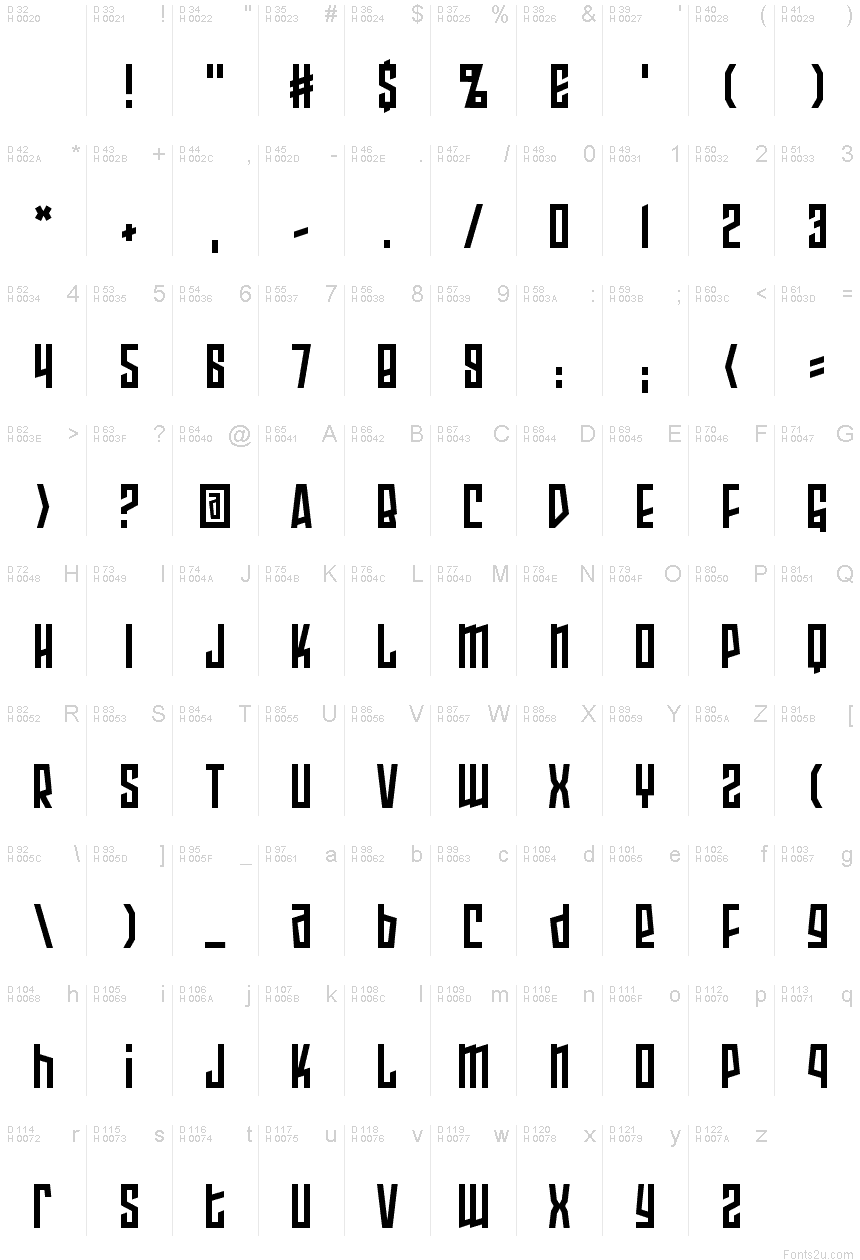
Armor Piercing 2.0 BB od Nate’a Piekosa to darmowy, retro font display o ostrym, arcade'owym charakterze. Wysokie, kanciaste kształty i ciasny, mechaniczny rytm nadają każdemu słowu wygląd tłoczonego metalu – jest odważny, zwarty i nieco drapieżny, przypominając opakowania starych gier lub komiksowe efekty dźwiękowe wycięte z czarnego winylu.
Armor Piercing 2.0 BB świetnie sprawdza się na okładkach komiksów, w grafice esports, tytułach plakatów, menu gier, miniaturach YouTube, projektach naklejek i na merchu. Ten darmowy font zachowuje wyrazistość w dużych rozmiarach, gdzie jego masywne kąty pozostają ostre i dominujące; zestaw go z prostym krojem bezszeryfowym w tekście głównym, aby tytuł przyciągał całą uwagę.